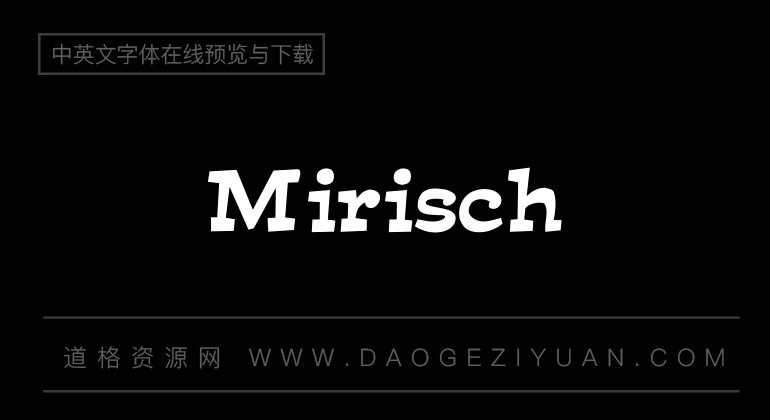
Mirisch 字体是一种细腻的衬线字体,由 Mirisch 公司设计,它是一种新的、柔和的衬线字体,具有清晰的字形和明确的细节。它的设计元素源自西方古典和现代设计,在细节上更加精细,可以满足多种文字表达的需求。它的特点是精致的字形,优美的曲线,柔和的线条,以及明确的细节。它可以用于多种文字表达,如商业广告、印刷品、网页设计等。内容介绍
Mirisch是一款非常不错的手写艺术字体,具有很好的视觉感,适合于文化类的宣传设计、商业类品牌的广告和产品包装设计以及个性化文字排版等较多场景。